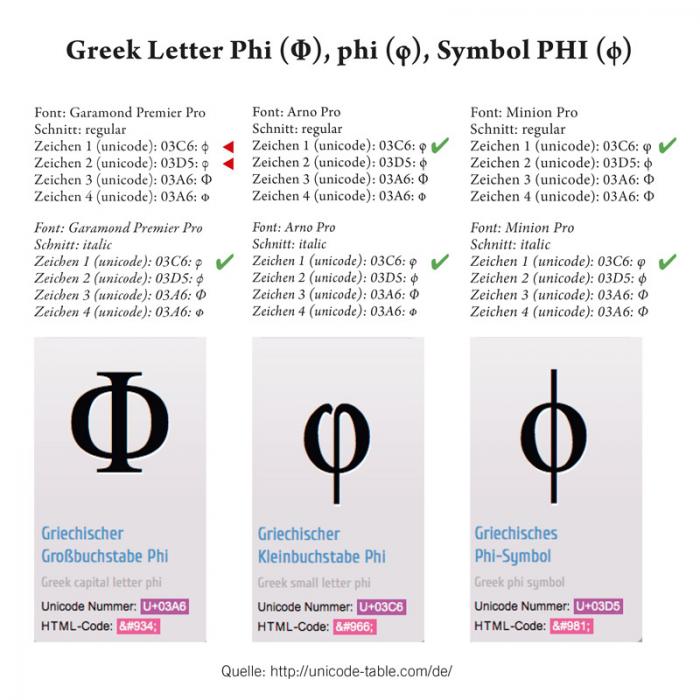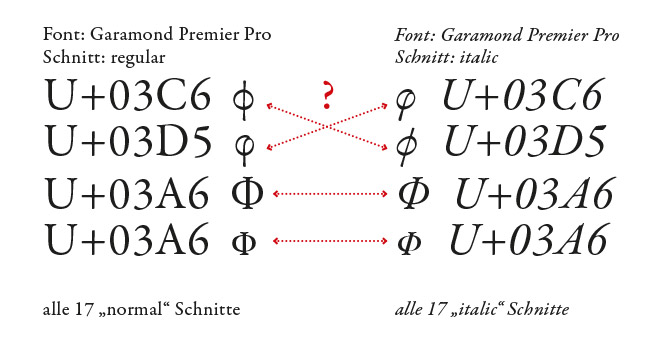
Fehler in der Zeichenbelegung in der Adobe Garamond Premier Pro
ich bin im Moment etwas ratlos und benötige euren Experten-Rat.
Es geht um das Symbol PHI (U+03C6) und den griechischen Buchstaben phi (U+03D5)
die beiden sind offensichtlich vertauscht worden.
Font: Adobe Garamond Premier Pro, Schnitt regular (italic ist ok) siehe Anhang.
Es geht um ein relativ umfangreiches Mathebuch.
Das Zeichen PHI kommt sowohl im Text, als auch in Formeln vor.
Was würdet ihr mir raten ?
1) Bei der Garamond Regular bleiben und Buchstaben gegenseitig austauschen
2) Nur bei dem Symbol den Schnitt italic verwenden
3) Eine andere Schrift verwenden, wenn ja welche?
4) Alles hinschmeißen und weinen?
5) Darauf hoffen das Adobe den Fehler rasch behebt - und veröffentlicht
das ist meines erachtens kein fehler, sondern eine bewusste designentscheidung. sowohl die form mit durchlaufendem strich als auch die form mit schleife sind akzeptable glyphische varianten des kleinbuchstaben-phi (siehe auch hier). die schleifenform ist für den buchstaben gängiger, aber robert slimbach hat sich bei der garamond premier offensichtlich entschieden, der anderen form – anders als bei der arno oder der minion – den vorzug zu geben. arno und garamond premier enthalten beide formen, die minion nur die schleifenform.
arno: gerade vs. schleife
garamond premier: gerade vs. schleife
bei der arno kann man in geeigneter software die gerade variante als formatsatz 6 aufrufen; in der garamond premier kriegt man die schleifenform über den formatsatz 2. einige andere fonts, die ich kenne, bieten dieselbe möglichkeit, zwischen den formen hin und her zu schalten. wenn du in einer anwendung arbeitest, die nicht auf formatsätze zugreifen kann, aber diese phi-form brauchst, müsste man mal schauen, was sich machen lässt.
ps: das phi-symbol der ff dax sieht, bei aktiviertem formatsatz 3, übrigens so aus :-D
danke für die rasche rückmeldung. verwirrt bin ich nur das in allen italic schnitten die eine form verwendet wird - in den normalen schnitten - die andere form. arno pro und minion pro (und alle anderen schriften die das phi-symbol haben) sind in sich konsistent. auch die dax.
dass alle anderen schriften konsistent sind, stimmt nicht (spontanes gegenbeispiel: ladoga). ich kann nur vermutungen anstellen, warum robert slimbach sich in der aufrechten für die gerade form und in der kursiven für die schleifenform entschieden hat: generell sind kursive schnitte oft chirographisch geprägt, erinnern also stärker als ihre aufrechten gegenstücke daran, wie buchstaben mit der hand geschrieben werden. vielleicht fand slimbach die schleifenform, die mit einem federzug geschrieben werden kann, zu handschriftlich für seine aufrechte, aber genau richtig für die kursive. du hast vielleicht gesehen, dass der formatsatz, mit dem man das schleifen-phi hervorholen kann, bei der garamond premier auch zwei weitere alternativen aktiviert (theta: normal vs. alternativ; kappa: normal vs. alternativ). die alternativformen sind in der kursiven wiederum standard. auch hier ist der unterschied, dass die standardform der aufrechten ein absetzen des stifts erfordert, während die kursive standardform in einem zug geschrieben werden kann. ein bisschen erstaunlich finde ich slimbachs entscheidung deswegen, weil die griechischen buchstaben der garamond premier (aufrecht wie kursiv) generell viel kalligraphischer gezeichnet sind als die der minion oder der arno und auch stärker mit den lateinischen buchstaben konstrastieren. wenn, dann hätte ich bei der garamond premier erwartet, dass auch die aufrechte die in einem zug geschriebenen formen als standardglyphen hat – aber vielleicht ging slimbach das gerade den entscheidenden schritt zu weit.
ich möchte das design der schrift, die zeichenform garnicht infragestellen - beide zeichen (alle 4) sind wunderbar gelungen. nur das sie zwischen den schnitten die position im unicode wechseln.
Vielleicht kannst du damit etwas anfangen:
In der Garamond Premier Pro ist das Zeichen ebenso wie in der kursiven zweimal belegt. Beide Schriften haben die gleiche Zeichenbelegung.
Einmal unter
U 03D5 Greek Phi Symbol
und auch unter
U 03C6 Greek Small Letter Phi
So ist die Zeichenbelegung zumindest in dem mir vorliegenden Font. Die Schrift wurde ca. vor einem Jahr lizenziert.
wow. adobe reagierte superschnell.
I confirm that this was a bug in version 1.014 of the family, which got fixed in the next major version (2.x).
The italics are correct. The bug affects only the phi symbol (U+03D5) of the upright styles; the shape of that character should resemble a circle with a vertical bar through it.
The shape of the italic phi letter (U+03C6) without the vertical stroke above the x-height is "as designed".
It seems like you have the older version of the family.